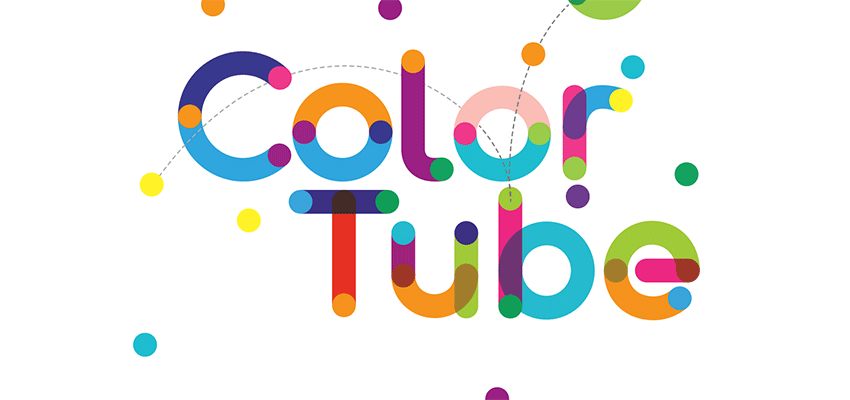
Webデザインにインパクトを与える デザイン性の高い英語フリーフォント14選
Three.js、split layouts、micro-interactionsやgradientsなどの多くのトレンドにもかかわらず、タイポグラフィーはいつも気にかかる存在です。タイポグラフィーを使わなければウェブサイトを作り上げられません。写真は千の言葉ほどの価値があるかもしれませんが、ちょっとした説明文がなければ、本当に写真のみになってしまいます。好むと好まざるとにかかわらず、タイポグラフィーはかけがいのないものなのです。
デザイナーはほとんど毎日フォントを扱います。キャッチーなスローガンに使ったり、ブロックヘッドラインに使ったりと様々でしょうが、フォントは注意深くそして内容に合ったものを選ぶべきです。毎日使う文字のような場合には、必ず、その文字を使うことでいっそうクリエイティブになるようにすべきです。
結果として我々ユーザーは、様々な字体を見ることになります。それはまるで、豊富な種類のドレスで着飾った文字たちの舞踏会のようです。この豊富なドレスとはつまり、クリエイティブで洗練されたフォントのことです。フォントは強烈な印象を与えたり、全体の美しさを整えたりすることで、プロジェクトに利益をもたらしてくれます。もしあなたが次の舞踏会用にアーティスティックな印象のドレスを探しているならば、本記事を読んでみてください。他と被らない、あなたのウェブサイトを目立たせてくれるような14個の無料フォントをご紹介します。
Colortube
Colortubeはすべてカラフルなフォントで、目立ちます。カラフルなフォントは最近とても話題です。もしあなたが流行りに乗りたいなら、これを試してみるべきです。このフォントは多くのプロジェクトに適している目に楽しい、なめらかな文字の形をしています。特別にトーンを混ぜることで文字をダイヤモンドのように輝かせることができるので、PhotoshopやIllustratorを使ってみてください。
Secure 3D Letterings
MIIMのSecure 3D Letteringsはとくにクールなデザイン向けに作られました。最近ではクールなデザインがとても人気です。リアルで粗野な感じがします。金属的に見える質感は素晴らしく、等間隔に置かれたボルトが全体の見た目をまとめてくれています。これはプロジェクトにクールさを加えたい場合や風変わりなデザインの中で目立ちたい場合に理想的なフォントです。
Marquee Light Bulbs 3D Numbers
もし金属のようなフォントがやりすぎていると感じる場合には、電球付きのリアルなフォントを試してみてください。ヴィンテージなタッチなため、レトロなプロジェクトにぴったりです。唯一の欠点は、無料バージョンが数字にのみ適用されている点です。
Gilbert Free Animated Typeface
ぱっと見、Gilbertは上記で紹介したColortubeとほとんど同じように見えます。一つの文字の中に様々な色を重ねて使用するというColortubeと同様のアプローチを基本としているためです。しかし、ポイントはこれが動くフォントだということです。動きのチャーミングさとエネルギッシュな見た目を上手に併せているため、次のプロジェクトにぴったりのフォントだと思います。
Font Balloon
Font Balloonはエレガントさと筆で描いたようなスタイルの目を引くような融合と幾何学模様のような細かさが上手に文字になっているフォントです。Aga Magdziak氏が上手に色を選択したため、すべての色がきれいに表れています。彼女はまた、デザインを仕上げられるように、付属のパターンセットも提供してくれています。
Airfool Free Display Typeface
では次に、Airfool Typefaceをおすすめします。このフォントは単色ですが、かわいらしい風船モチーフのデザインや、ビビットなカラー、あそび心あふれる文字のおかげで、この記事で紹介しているほかのカラフルなフォントに負けていません。
Fistura
カラフルなフォントというと、最初に思いつくのがキラキラした80年代のデザインです。ディスコ、MTVやきらきらしたスパンデックス素材のパンツが大好きなエアロビックスターなどです。Fisturaはこの時代に人気だったものをデザインに取り入れています。明るいカラーリング、ネオン、様々な幾何学模様が一つにまとまっています。このような80年代らしさがこのフォントをユニークでとても魅力的なものにしています。
Neon Font
Neon FontはAga Magdziak氏のもう一つの傑作です。彼女は、カラフルな文字が、魅力的でアーティスティックなスマートさを持っているということ証明しました。このフォントの美しさは筆で描いたようなタッチからも出てきていますが、寒色を用いたことで出たツヤ感も魅力を引き出しています。このフォントをダウンロードすると、ボーナスとしてパターンのパックが一緒についてきます。
Aemstel Free Layered Font
Aemstelは層になったフォントでプレーンバージョンもフェイク3Dバージョンもどちらも素敵です。内側や外側に派手なオプションがついているものなど、5個のスタイルを無料でダウンロードできます。ドラマチックな効果を生み出せるので試してみてください。
Invertor
もともとPrint Mediaで作られたこのInvertorはポスターやフライヤー、雑誌の表紙のタイトルやスローガンを美しくするためのフォントです。もちろんウェブデザインでも使えます。液体のような見た目が印象的です。
Pikolo Block Alt
ラインアートの代表として、Pikolo Blockはそのルーツに忠実に、シンプルな幾何学模様の形からフォントを形成しています。しかし、粗野でも野蛮でもありません。反対に、洗練されたカーブやスムーズなアングルのおかげで、上品な印象です。
Lux Lineae
Lux Lineaeはもう一つのセンスのよいラインアートフォントです。以前の例は少し線の幅が狭かった印象でしたが、Stephane P氏によって作られたこのフォントは十分な幅があります。エレガントに見えますし、洗練された感じがします。
Seg Ment
Seg Mentもまたラインアートからその美しさを取ってきています。しかし、線の幅をとても広くとったことで、テクノのような、また少しクールな見た目になっています。ハイテクな調子のウェブデザインを行うときの理想的なパートナーです。
Scritus Typeface
マルイ角とラインの最後が、このフォントの美しさの元です。幾何学的でかろうじて文字と読めるようなデザインです。この記事で紹介した他のものとは違い、未来的な印象を受けます。4コラムで使用できるバージョンと標準的なフォーマットが利用できます。
デザインに洗練さを加えてみよう
洗練されたデザインのフォントは注意をひいたり、メッセージを届けるために素晴らしく有効です。いつも何か、従来のフォント以上のものを提供してくれます。